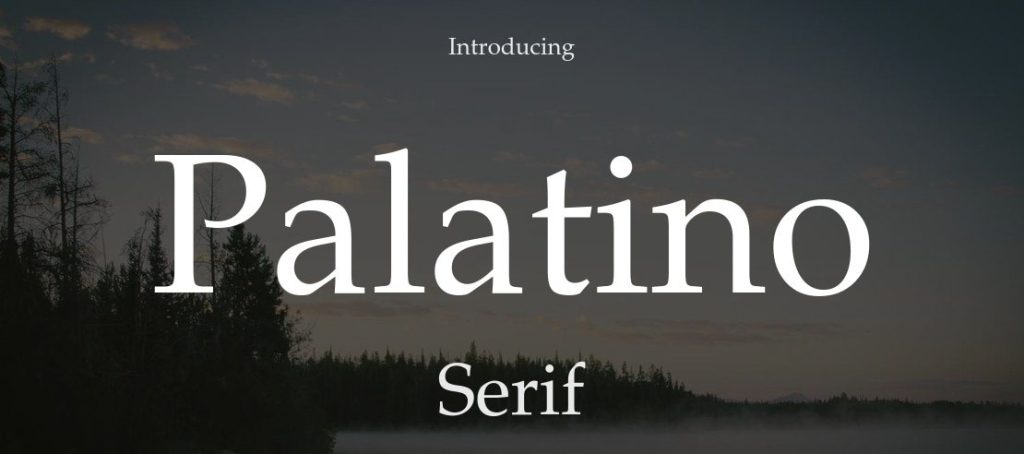
Tác giả: Hermann Zapf
Ngày phát hành: 1949
Ngôn ngữ: Tiếng Anh
Bộ Font: Chưa rõ
Phân loại: Thanh lịch
Kiểu chữ: Serif
Palatino Font được lấy cảm hứng từ các phong cách chữ viết tay và kiến trúc của thời Phục hưng. Palatino Font thuộc bộ font chữ có chân. Palatino Font mang một vẻ đẹp cổ điển và thanh lịch, phù hợp với các tác phẩm văn học, tài liệu học thuật và các ấn phẩm in ấn cao cấp. Với những nét chữ mềm mại, cân đối và sự kết hợp hoài cổ giữa các đường nét, thể hiện một phong cách đầy tinh tế và thanh nhã. Nhờ đó mà phông chữ này, đã trở thành lựa chọn ưa thích của các nhà xuất bản, nhà văn và các nhà thiết kế.